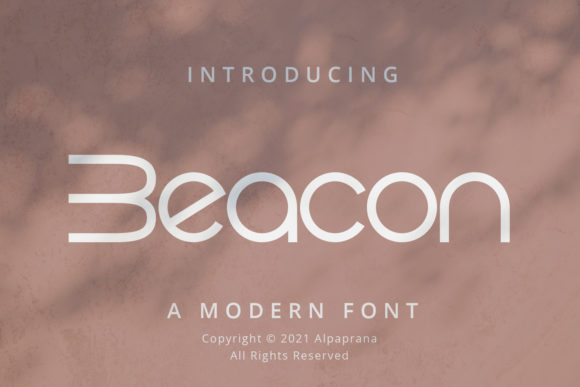
[Creativefabrica] Beacon Font (2021)
Beacon - это минимальный и техно-дисплейный шрифт.
Его можно легко подобрать к невероятно большому набору проектов, поэтому добавьте его в свои творческие идеи и обратите внимание на то, как он их выделяет!